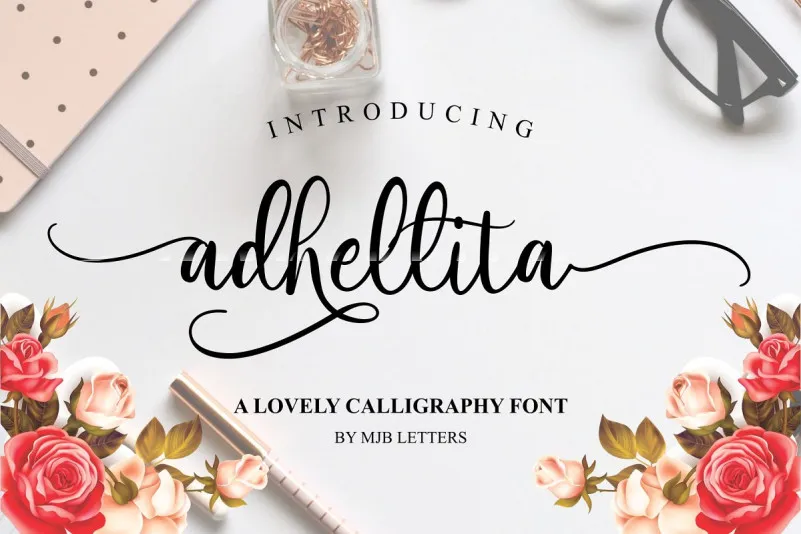
Adhellita Script Font – Download Grátis
Aqui está uma versão em português do Brasil para a descrição solicitada: Descobrimos uma maravilha neste novo adhellita font script! Esta é uma deliciosa fonte de caligrafia que se tornou disponível gratuitamente para download. Ela traz o charme e sofisticação da tipografia de caligrafia, com suas incríveis curvas e alternativas únicas. Este tipo de letra vai adicionar um toque inovador a qualquer projeto! Perfeito para seus projetos estaçãoais futuros, artesanato, casamentos, negócios ou até mesmo para os posts nas redes sociais. Adellita é uma escolha fantástica para enriquecer seu design. Faça o download e experimente esta fonte incrível hoje mesmo!